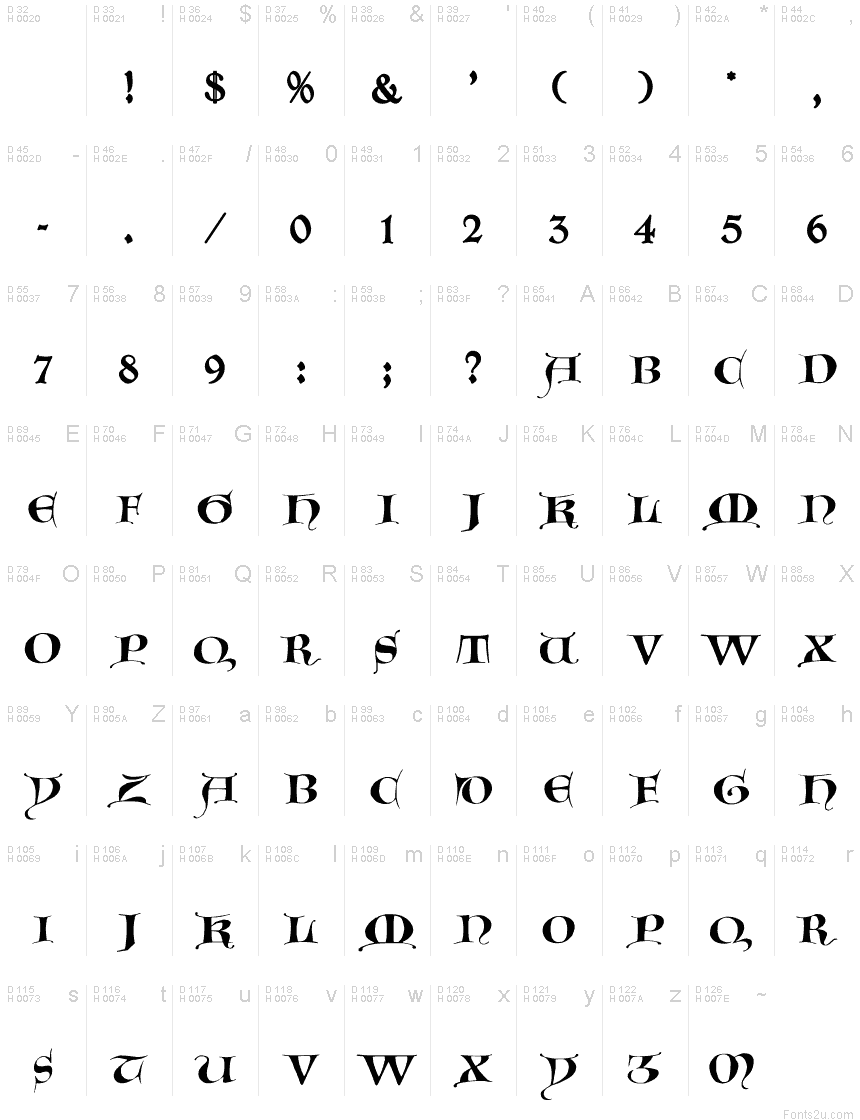
Gotische Majuskel autorstwa M. Kleina to darmowy średniowieczny gotycki krój pisma, który wygląda, jakby został wyjęty prosto z XIII-wiecznego rękopisu. Szerokie, nasycone tuszem pociągnięcia pęcznieją i zwężają się w zahaczone końcówki, a zaokrąglone światła liter sprawiają, że całość jest bogata i czytelna, a nie surowa. Litery sprawiają wrażenie rzeźbionych, a nie pisanych, co nadaje nagłówkom ceremonialny, niemal liturgiczny charakter.
Dzięki Gotische Majuskel możesz nadać autentyczny, starodawny głos okładkom książek fantasy, podręcznikom RPG, plakatom LARP, logotypom zespołów metalowych, oprawie wydarzeń historycznych i certyfikatom. Ten darmowy font świetnie sprawdza się w dużych nagłówkach lub krótkich hasłach; niech gra pierwsze skrzypce, a jako tekst pomocniczy wybierz czysty, bezszeryfowy krój, aby uzyskać wyraźny kontrast.